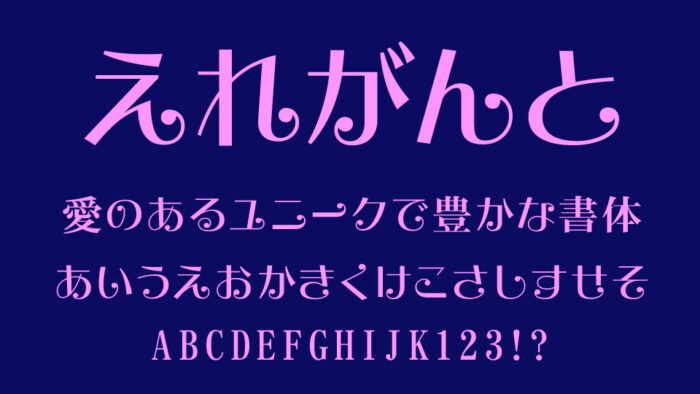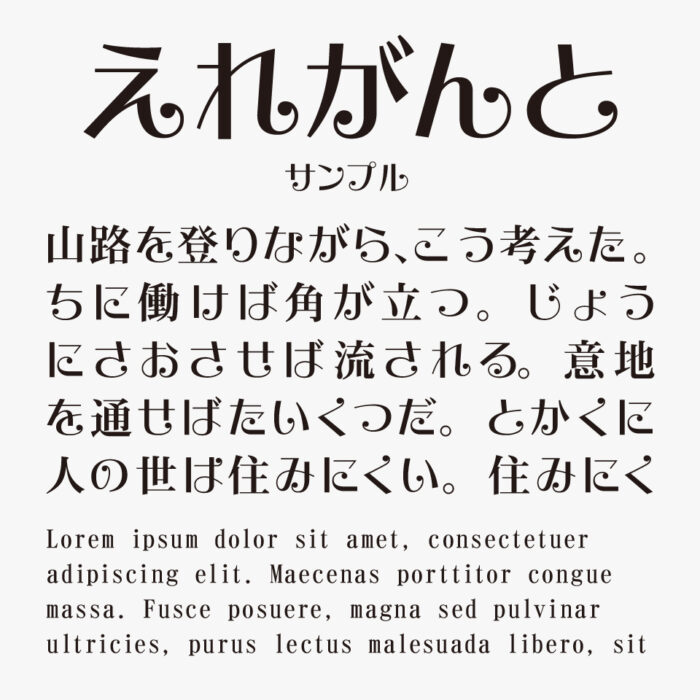
えれがんと平成明朝
えれがんと平成明朝フォントは、かな文字の一部にクルンとした丸いアクセントがついた、ご機嫌な雰囲気のある可愛らしいデザインフォントです。
マンガの吹き出しなどでは、お姫様やお嬢様が発しているセリフなどにも使われているので、高貴や上品などの雰囲気を感じれれるフォントです。
クリスマスやベルサイユといったちょっと特別感を表現したいときにぴったりです。